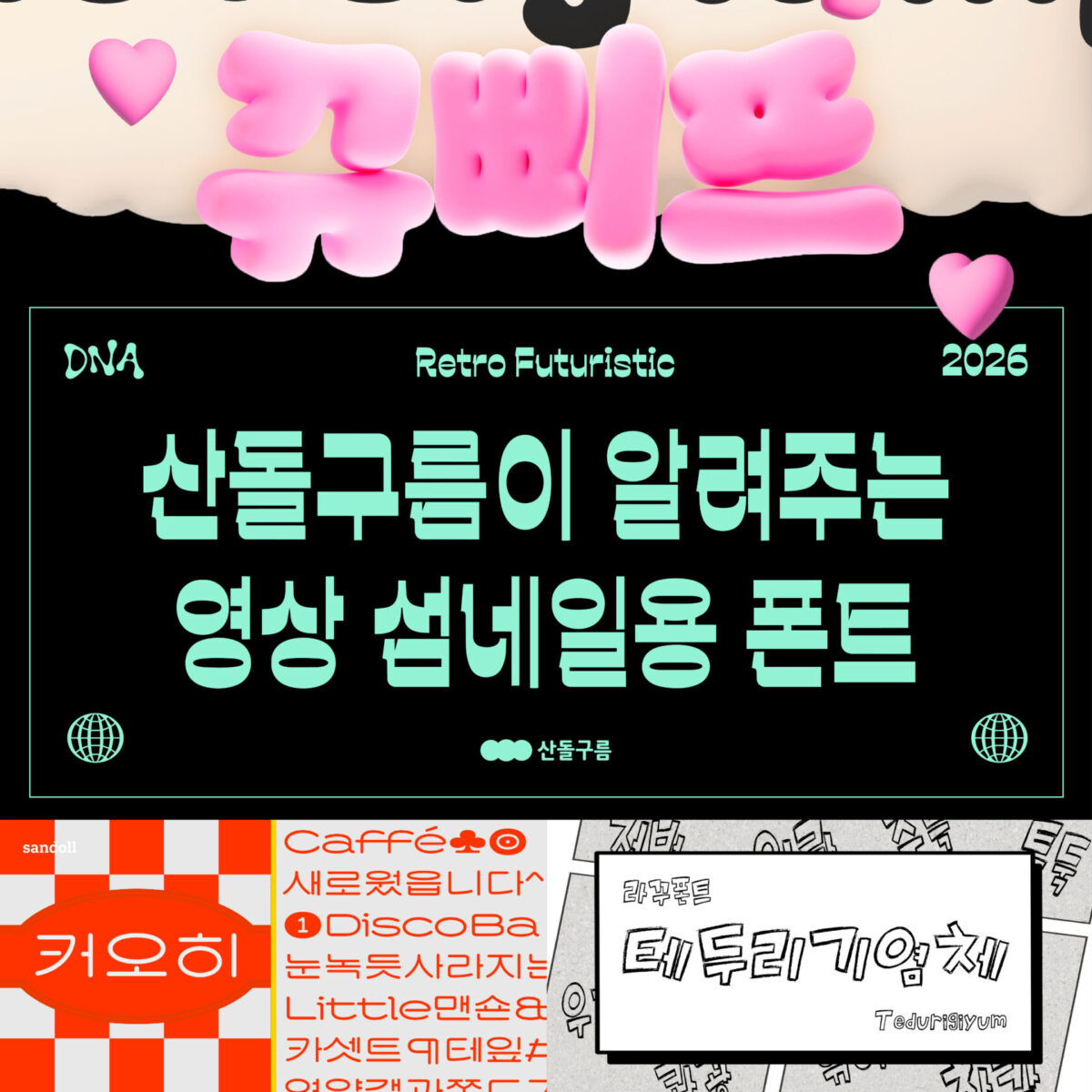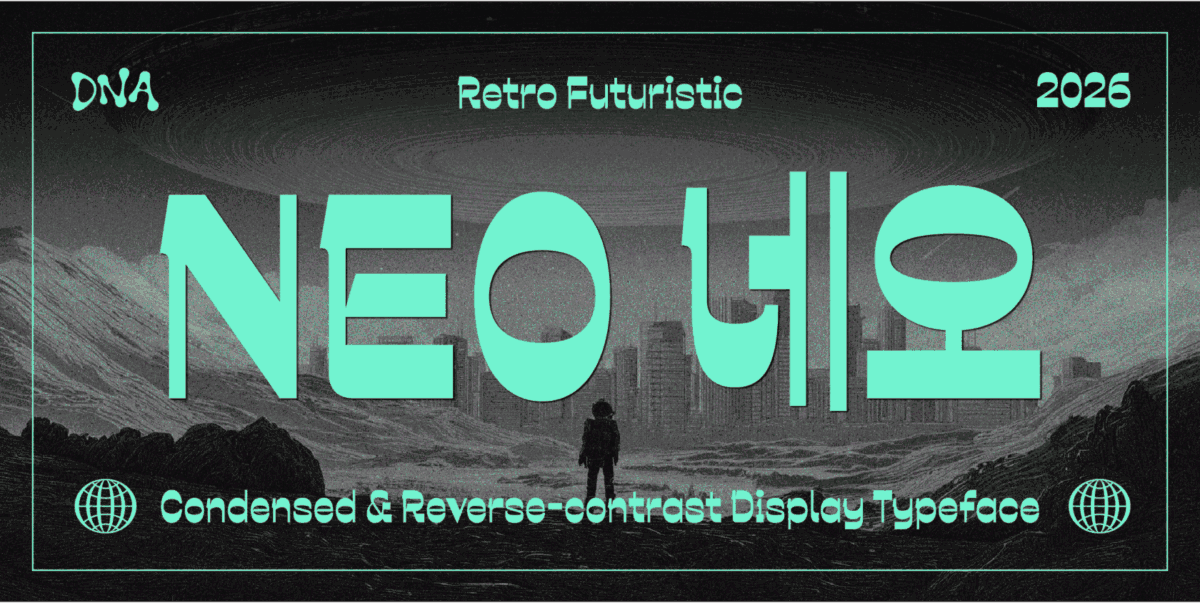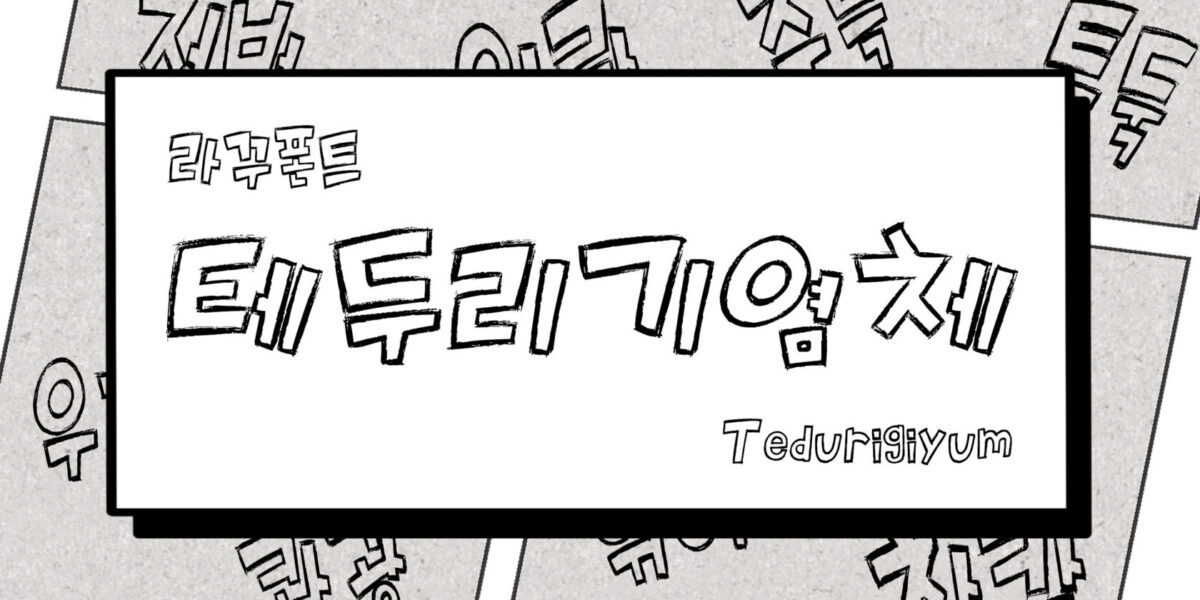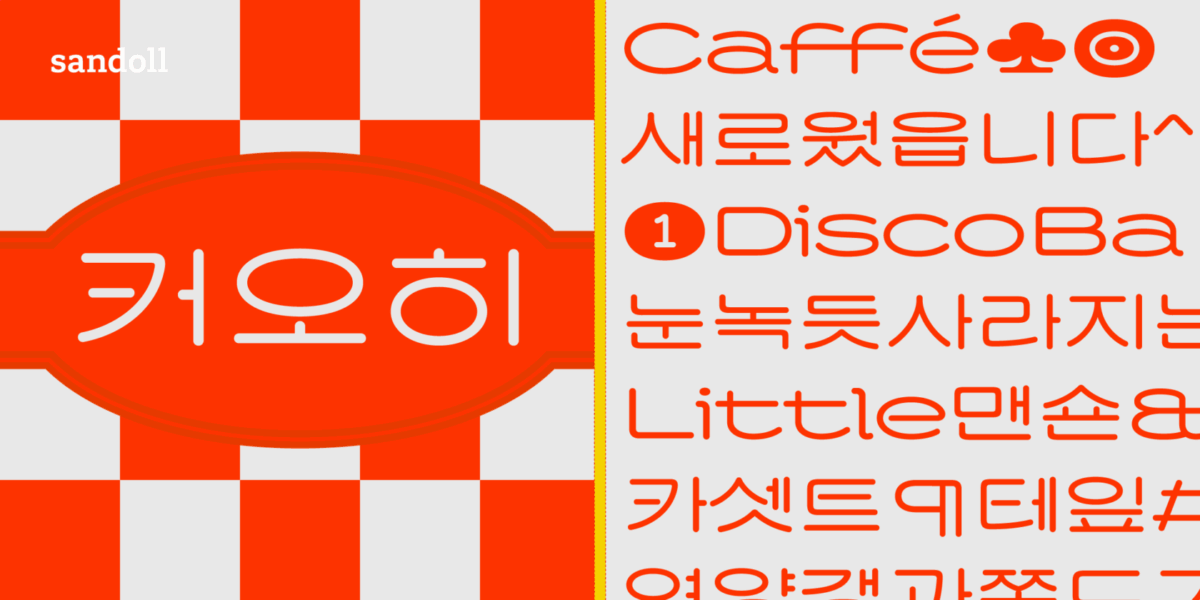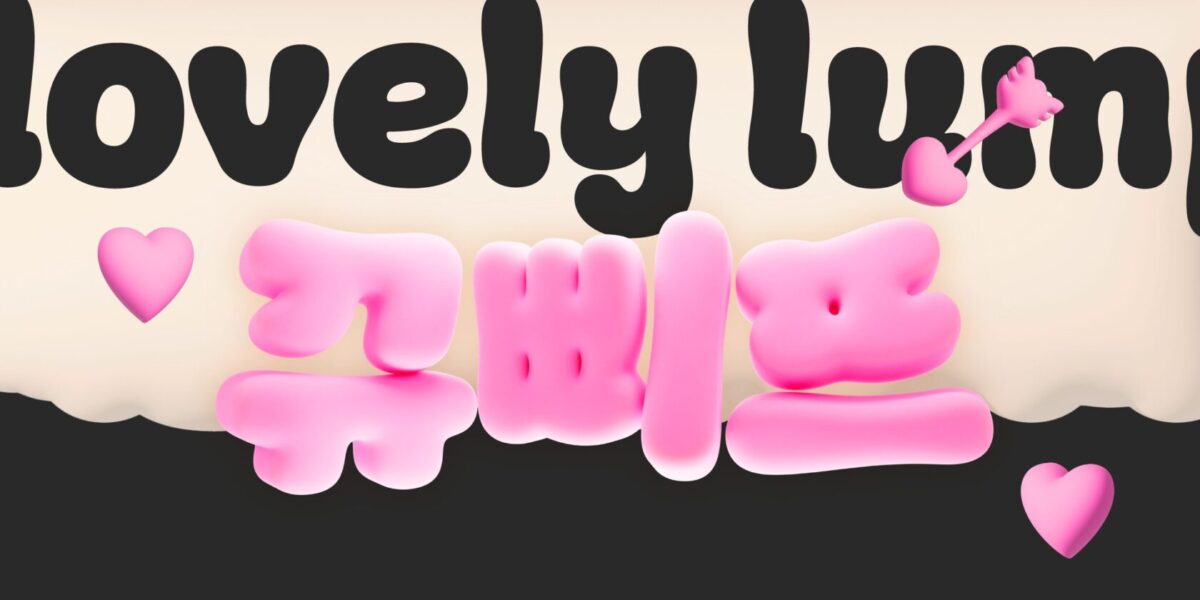
숏폼 섬네일에 쓸 폰트가 필요하다면? 산돌구름이 추천하는 영상용 폰트 4종
3초 안에 시선 고정과 클릭을 부르는 임팩트 폰트 추천
짧은 순간 안에 시선을 사로잡아야 하는 숏폼 콘텐츠에서는 섬네일의 역할이 무엇보다 중요합니다. 강렬한 첫인상을 만드는 폰트 하나만으로도 조회수와 체류 시간이 달라지기 때문입니다. 지금 소개하는 폰트 4종은 눈에 띄는 형태와 개성 있는 디자인으로, 콘텐츠의 주목도를 극대화하는 데 효과적입니다. 산돌구름과 함께 네일의 완성도를 높이고, 더 많은 클릭을 이끌어보세요.
1. 라꾸폰트 / RK-테두리기염체
이 폰트는 글자의 중심을 비우고 외곽선만 남긴 구조가 시선을 단번에 끌어당기는 디스플레이 폰트입니다. 둥글고 가벼운 윤곽선이 더해져 귀엽고 경쾌한 분위기를 자연스럽게 만들어는데요. 특히 배경과 조합했을 때 더욱 돋보이며, 섬네일에서 텍스트를 강조하는 데 효과적입니다. 복잡한 이미지 위에서도 형태가 살아나 가독성과 주목도를 동시에 확보할 수 있습니다. 릴스, 쇼츠 등 짧은 영상 콘텐츠의 네일에 특히 잘 어울리는 포인트 폰트입니다.
2. 윤디자인 / Yoon 뀨삐뜨
풍성한 볼륨감과 둥근 형태가 돋보이는 귀여운 스타일의 디스플레이 폰트입니다. 자소마다 유연한 리듬감을 갖고 있어 생동감 있는 인상을 전달하는 데 특화돼 있는데요. 때문에 밝고 사랑스러운 분위기로 브랜드의 친근한 이미지를 강화하는 데 적합합니다. 특히 MZ 타깃 콘텐츠나 감성적인 릴스 네일에서 높은 반응을 기대할 수 있습니다. 짧은 문구에도 확실한 캐릭터를 부여해 시선을 사로잡을 수 있습니다.
3. 산돌 / SD커오히
이 글씨는 레트로 감성을 현대적으로 재해석한 라운드 스타일 폰트로, 독특한 분위기를 연출합니다. 부드러운 곡선과 개성 있는 자형이 어우러져 한눈에 기억되는 인상을 남기고 특히 ‘ㅇ’의 형태와 짧은 곁줄기 등 디테일이 살아 있어 시각적 재미를 더합니다. 또 한글과 영문을 함께 사용할 때 균형감 있는 구성으로 네일 완성도를 높여줍니다. 트렌디하면서도 감각적인 콘텐츠에 활용하기 좋습니다.
4. DNA폰트 / DNA네오
획의 굵기 대비를 뒤집은 독특한 구조로 강렬한 인상을 주는 디스플레이 폰트입니다. 좁은 너비와 대비감 있는 형태가 결합되어 시선을 빠르게 집중시키는 효과가 있습니다. 일반적인 폰트와 차별화된 구조로 네일에서 확실한 존재감을 드러냅니다. 특히 강한 메시지나 강조가 필요한 키워드에 사용하면 효과적입니다. 임팩트 있는 제목이나 후킹 문구를 표현할 때 사용해보세요.